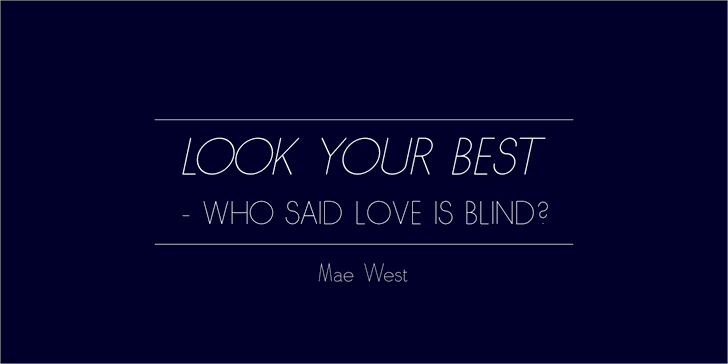
Estamos muito felizes por você explorar a SkarpaLT font, uma elegante sans serif para seus projetos digitais. Seja para criar um layout minimalista ou adicionar alguns toques de personalização, esta fonte oferece uma aparência fluida e moderna que certamente combinará perfeitamente em diversos ambientes. Nesta categoria especial de fontes sans-serif, o designer Hamilton criou uma opção única com traços finos e elegantes. O resultado é uma fonte suave e versátil, ideal tanto para aplicações corporativas quanto para design pessoal. A SkarpaLT oferece um toque atraente que complementará sua identidade visual de forma sofisticada. Para quem precisa da pro versão desta font (como pode ver na imagem acima), ou mesmo está interessado em licenças comerciais, Hamilton disponibiliza facilmente estas opções através de suas plataformas favoritas – Etsy, MyFonts e Fontspring. Com uma variedade de oportunidades para adquirir a SkarpaLT font, você encontra fácil acesso ao que precisa para usar esta elegante fonte em seus projetos digitais. Experimente a SkarpaLT hoje e descubra por si mesmo o encanto desta sans serif moderna. Seja para um projeto pessoal ou profissional, certamente vai adorar como ela se ajusta perfeitamente ao design.